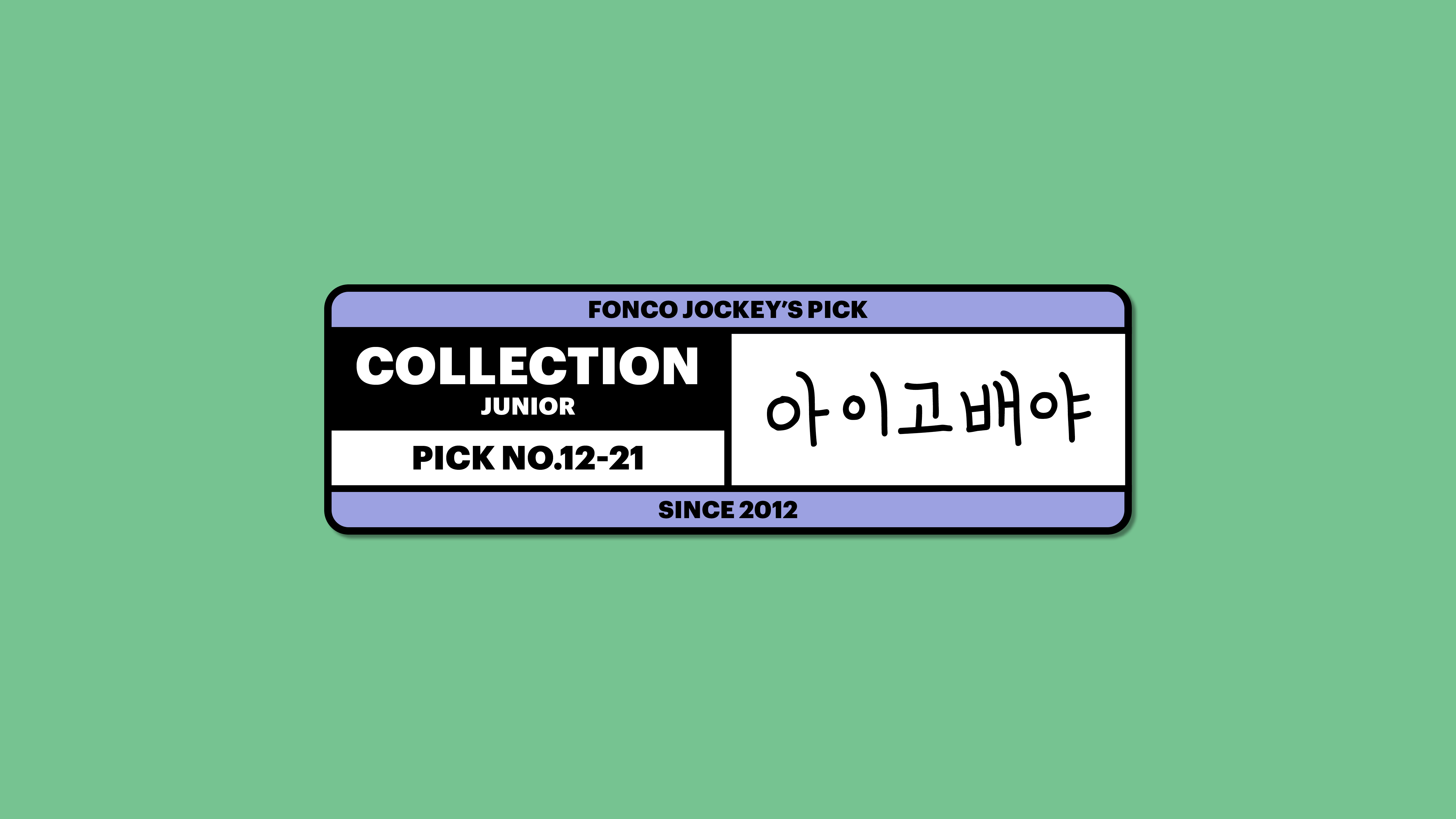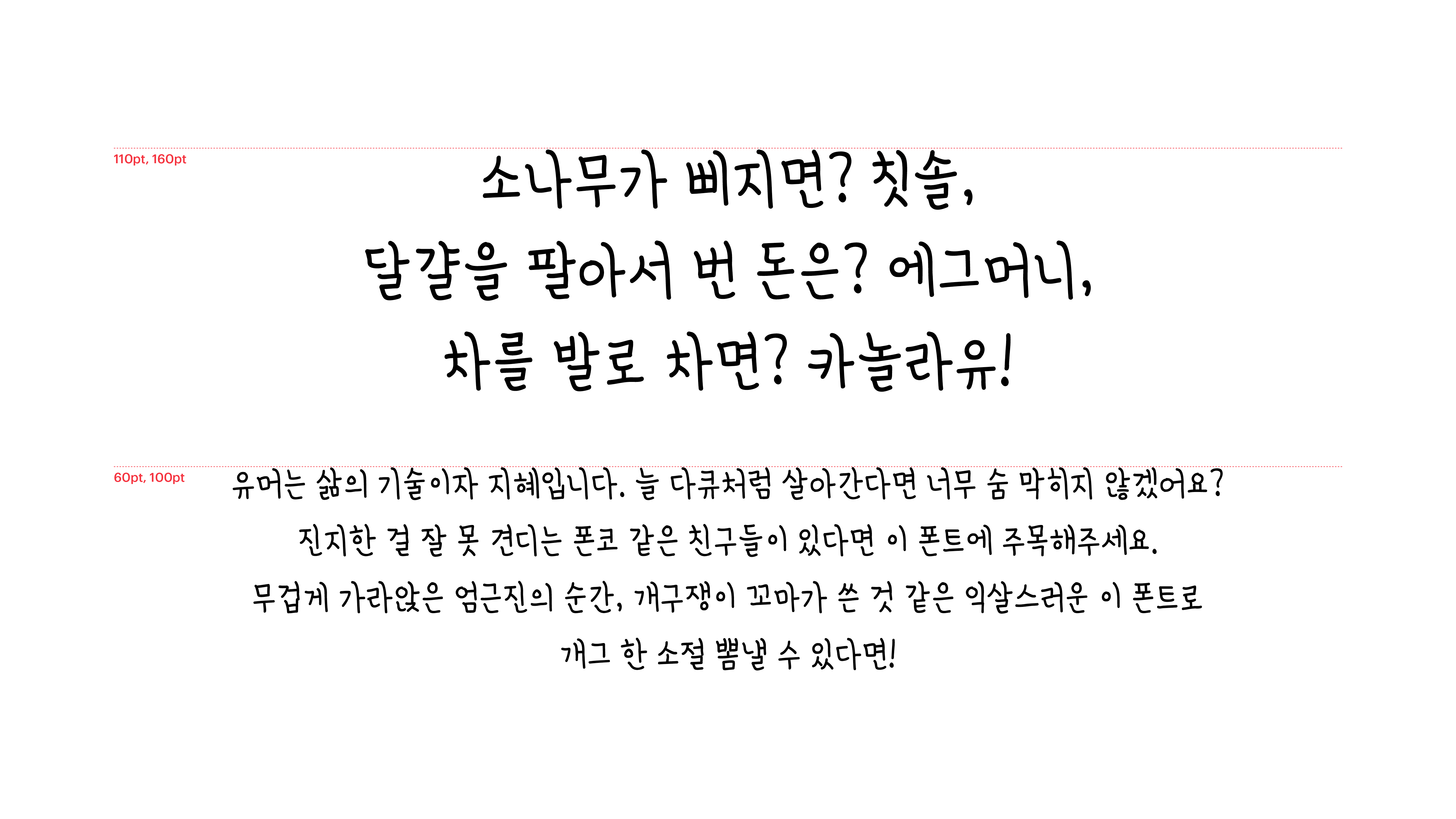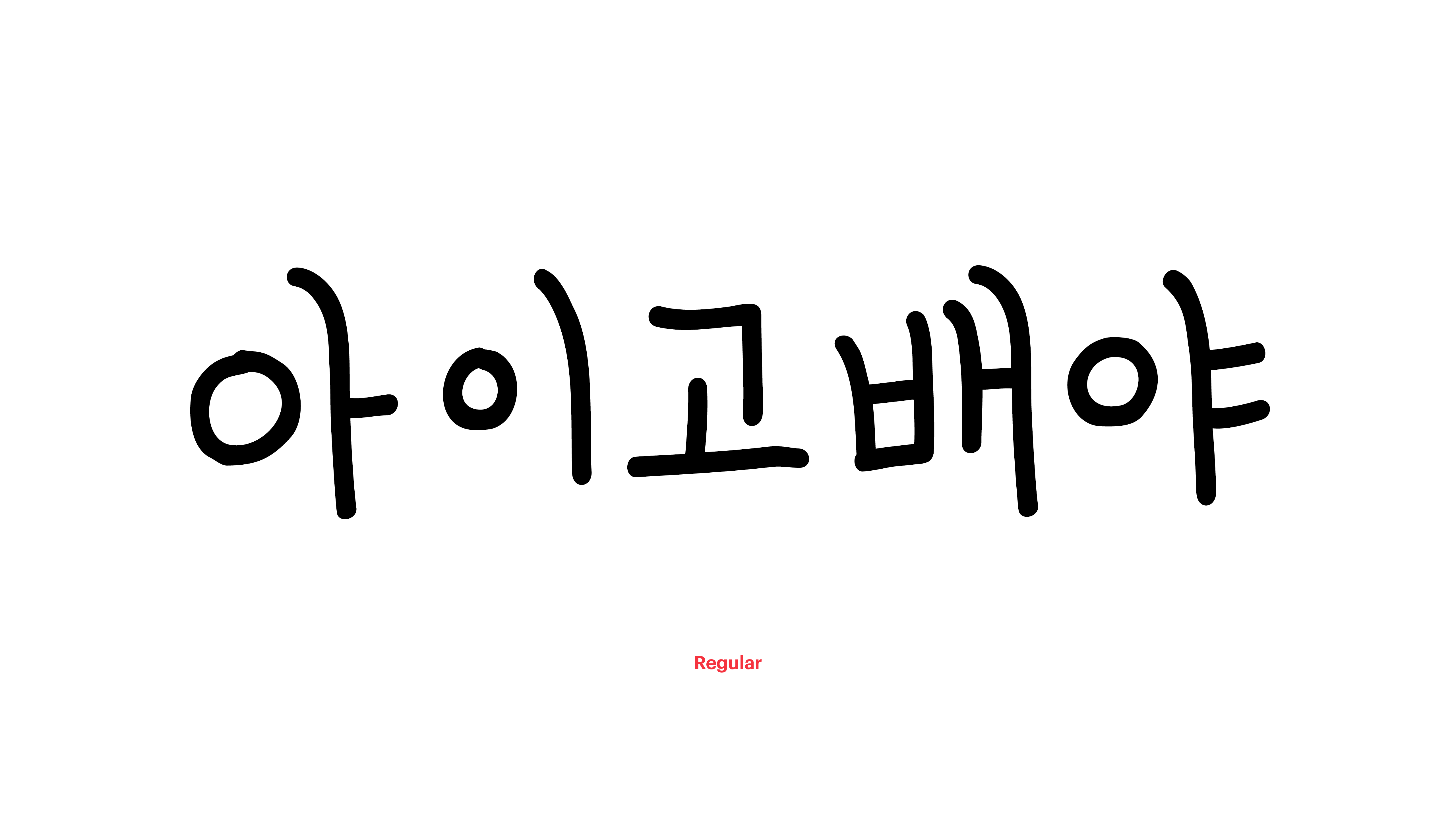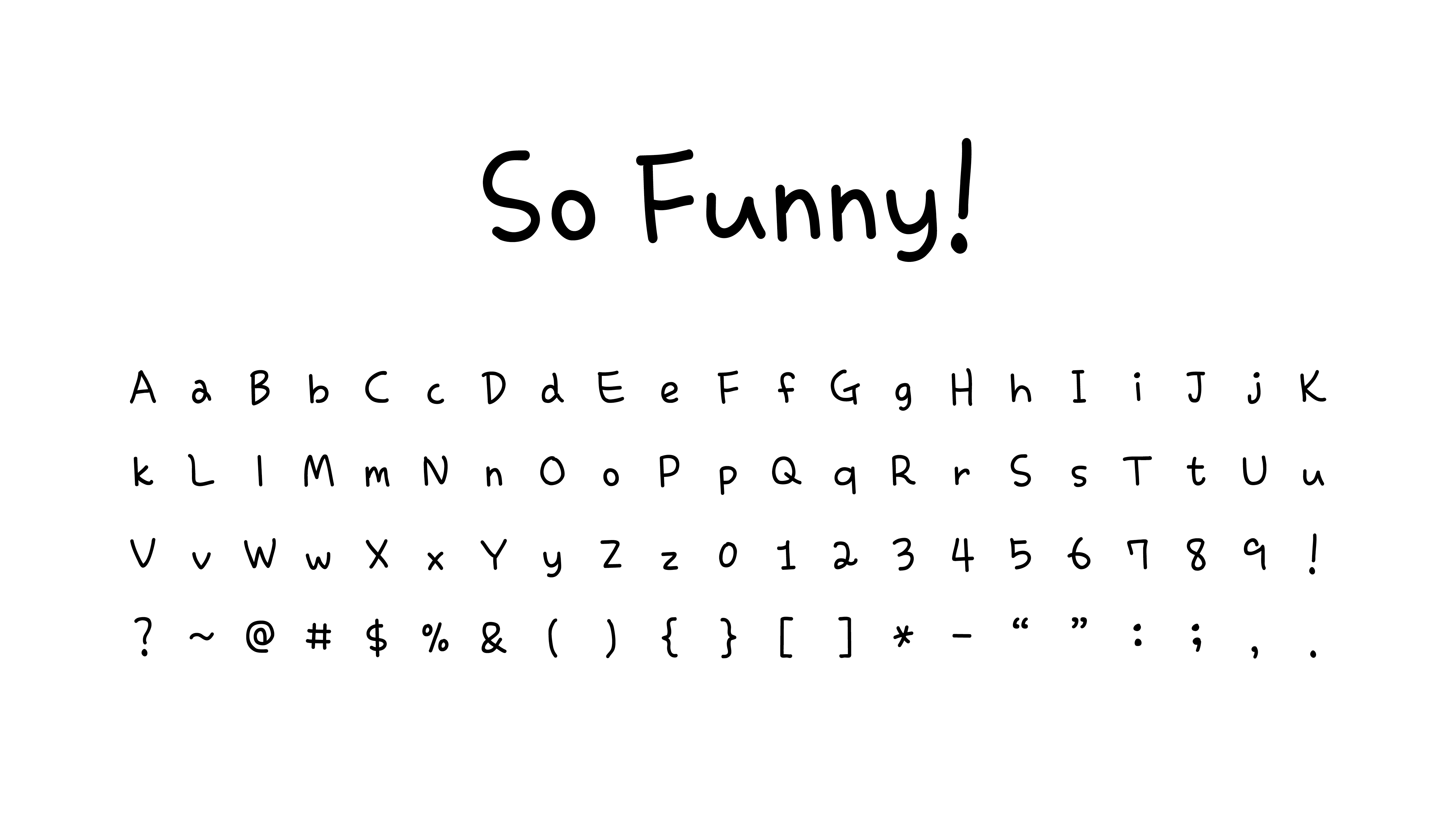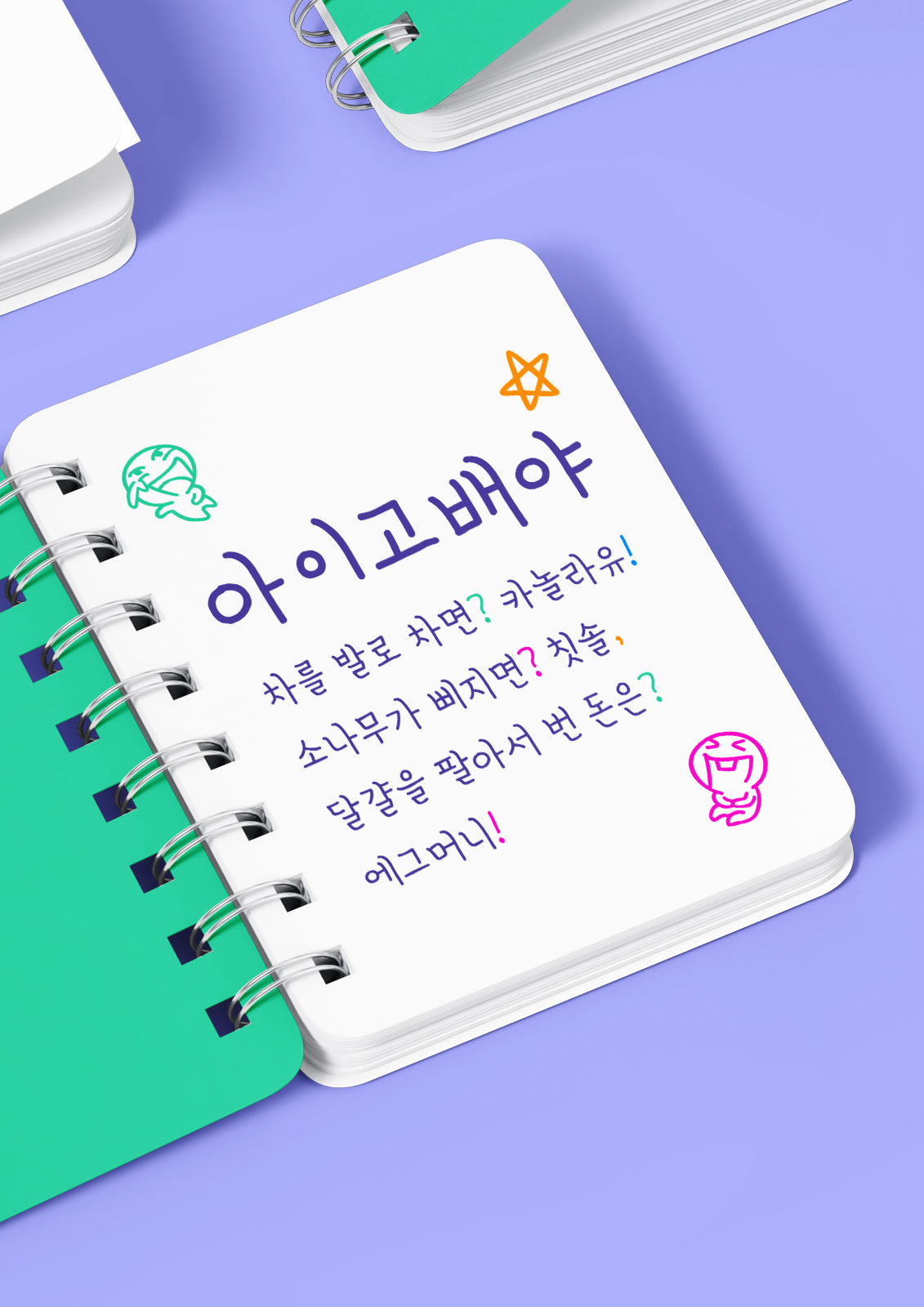
아이고배야
Yoon 아이고배야
유머는 삶의 기술이자 지혜입니다. 늘 다큐처럼 살아간다면 너무 숨 막히지 않겠어요? 진지한 걸 잘 못 견디는 폰코 같은 친구들이 있다면 이 폰트에 주목해주세요. 무겁게 가라앉은 엄근진*의 순간, 개구쟁이 꼬마가 쓴 것 같은 익살스러운 이 폰트로 개그 한 소절 뽐낼 수 있다면!